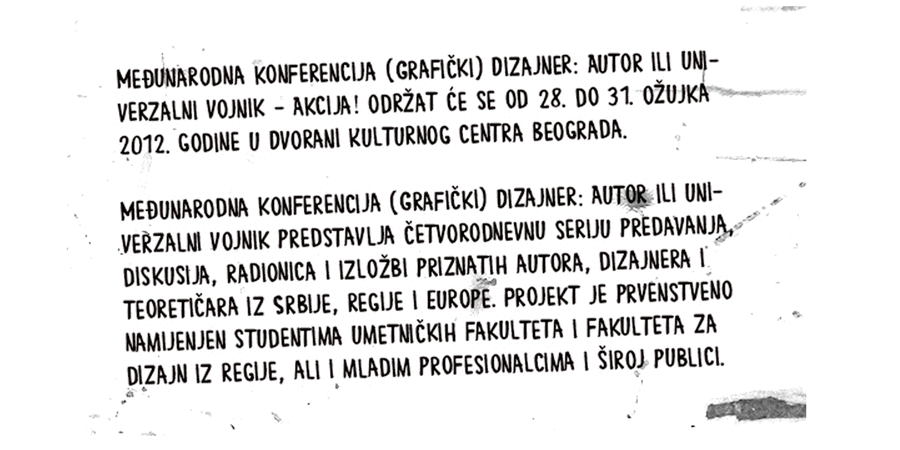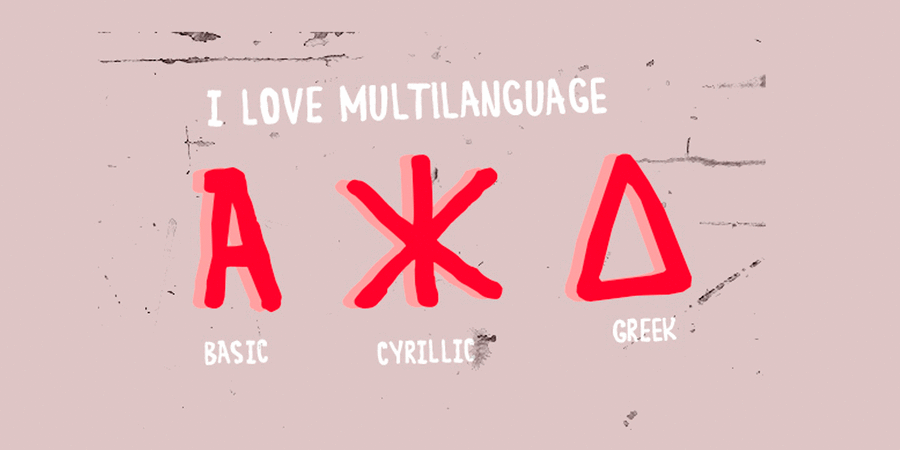
BRC – неформальний рукописний шрифт зі сміливим вуличним настроєм з підтримкою безлічі європейських мов, а також кирилиці та грецької. Цей шрифт має потужні можливості у вигляді альтернативних гліфів, розчерків та рідкісних лігатур. Шрифт BRC розробив Родріго Арая Салас у 2014 році.
Хіт 1990-х BRC підтримує 85 мовУкраїнська, Англійська, Німецька, Польська, Португальська, Іспанська, Французька, Грецька (сучасна), Грецька (стародавня), Російська, Чеська, Голландська, Італійська, Шведська, Турецька, Фінська, Білоруська, Грецька, Сербська, Болгарська, Естонська, Литовська, Албанська, Африкаанс, Баскська, Бретонська, Валенсаска, Galician, Гельська (Шотландська), Данська, Індонезійська, Ірландська, Ісландська (Win), Каракалпацька, Каталонська, Норвезька, Окситанська, Ретороманська, Самі Лулі, Тсванська, Узбецька (Лат.), Фарерська, фризька, Чаморро, Естонська (Win), Південносаамська, Албанська (Win), Угорська, Верхньолужицька, Карельська, Латвійська (Mac), Литовська (Mac), Маорійські (Mac), Молдавська (Лат.), Нижньолужицька, Румунська (Win), Словацька, Словенська, Туркменська (Лат.), Хорватська (Win), Естонська (Mac), Курдська, Латишська, Маорійські, Абазинська, Аварська, Агульська, Адигейська, Даргинську, Інгуську, Кабардино-Черкеська, Кабардинська, Карачаєво-Балкарська, Кумицька, Лакська, Лезгинська, Македонську, Мордовсько-Мокшанська, Мордовсько-Ерзянська, Ногайська, Рутульська, Табасаранська, Татська, Цахурська, Чеченська Функції сімейства шрифтів BRCЗастосування гарнітури у верстці:
Асоціації з сімейством шрифтів BRCОсобистість і характер гарнітури:
вуличний, побутовий, міський, сміливий, крафтовий, неформальний, мультяшний, ручний, економний, наївний, рукотворний, кустарний, саморобний, високий, оригінальний, живий, характерний, грайливий, помітний, домашній, виразний, неохайний, рухливий, непосидючий, ремісничий, хуліганський, потішний, милий, зухвалий, небезпечний, екстремальний, артізанальний, недбалий, кричущий, вернакулярний, динамічний, хлоп'ячий, нервовий, запальний